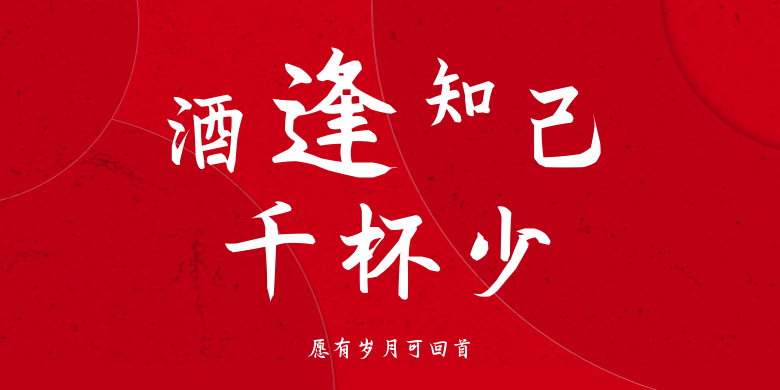
愿有岁月可回首
愿有岁月可回首,这款字体结构工整、笔画清晰,兼顾美观与易读性,适用于标题、正文、海报、包装、LOGO 等多种场景。字形优雅稳定,风格百搭耐看,适配日常排版与创意设计,让文字呈现更舒适、更具质感。愿有岁月可回首一笔一画,皆是细节,以均衡的比例、流畅的线条打造舒适视觉体验,字形端正大气,风格简约现代。无论是商业设计、品牌宣传还是日常排版,都能轻松驾驭,让文字更有格调与力量。愿有岁月可回首字体下载。